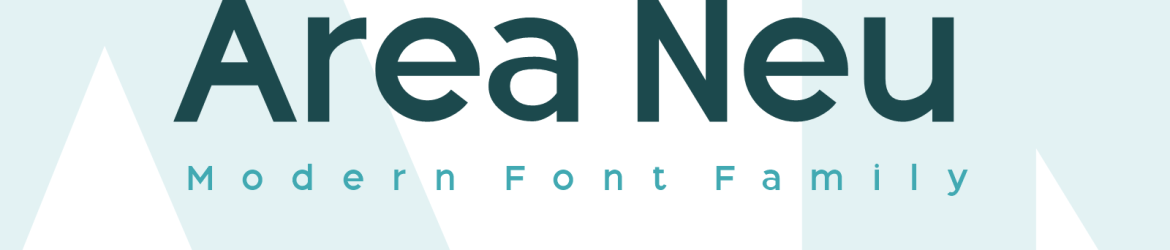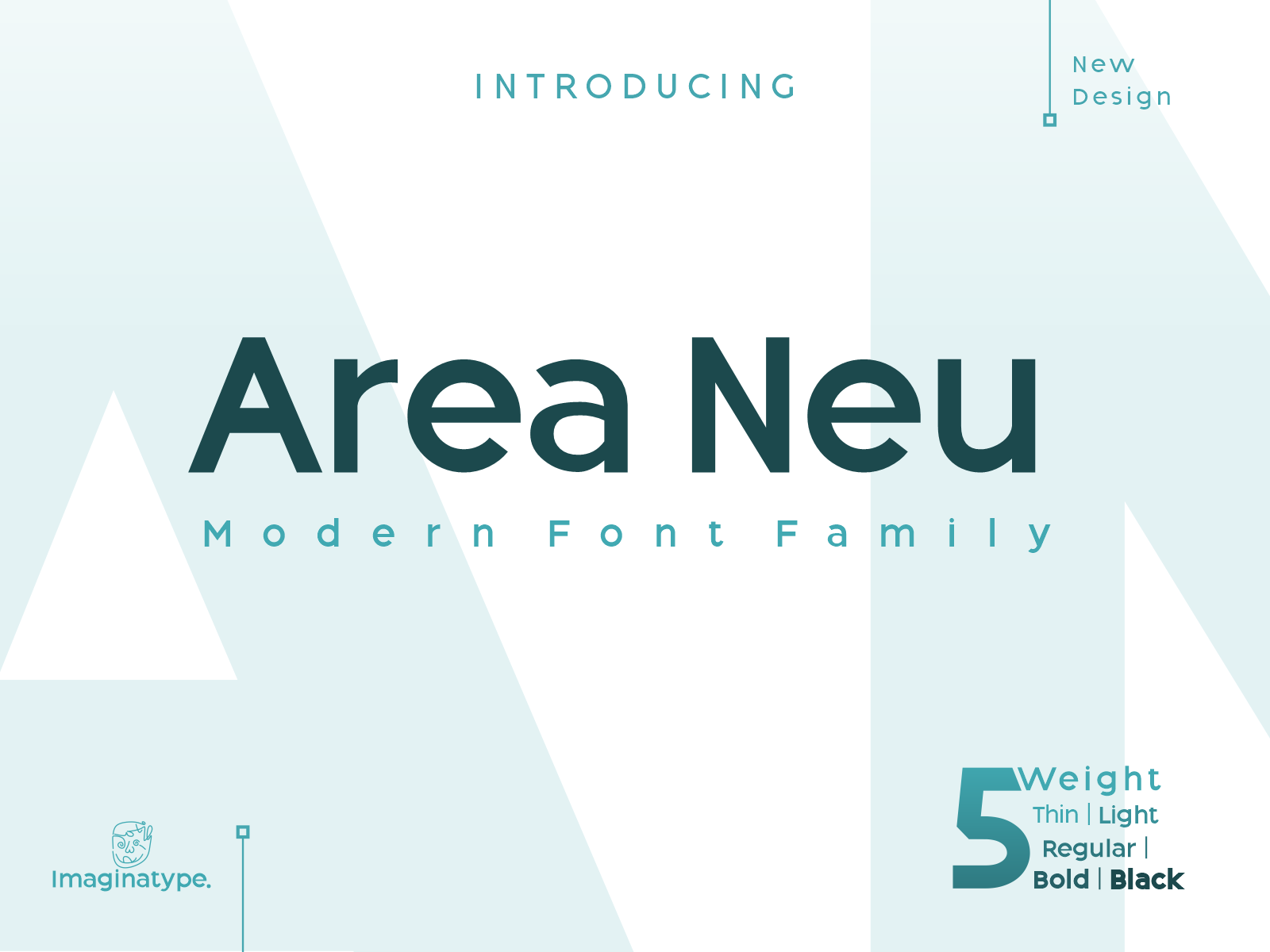
Area Neu Font – Fonte Grátis
Area Neu Font
A Área Neu Font é uma elegante fonte sans-serif que se destaca por sua modernidade e simplicidade. Composta em linhas retas e arredondadas com naturalidade, esta fonte garante um estilo único a qualquer projeto gráfico sem afetar o conteúdo do texto. Perfeita para aplicações digitais e impressivas, a Área Neu combina facilmente com outros tipos de letras, tornando-a uma escolha ideal para aumentar a qualidade dos seus projetos. Seja você criador de imagens digitais ou designer gráfico, a Área Neu é o amigo fiel que adiciona um toque moderno e atraente a qualquer texto. Como fonte sans-serif, esta opção permite que os elementos do design fiquem em destaque, tornando-a uma escolha irresistível para aqueles procurando adicionar um novo nível de sofisticação ao seu trabalho.